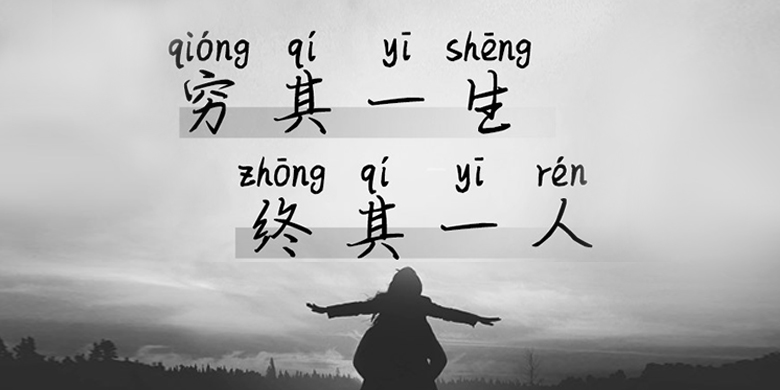
方正手迹-穷其一生终其一人
方正手迹-穷其一生终其一人,这款字体结构工整、笔画清晰,兼顾美观与易读性,适用于标题、正文、海报、包装、LOGO 等多种场景。字形优雅稳定,风格百搭耐看,适配日常排版与创意设计,让文字呈现更舒适、更具质感。方正手迹-穷其一生终其一人一笔一画,皆是细节,以均衡的比例、流畅的线条打造舒适视觉体验,字形端正大气,风格简约现代。无论是商业设计、品牌宣传还是日常排版,都能轻松驾驭,让文字更有格调与力量。方正手迹-穷其一生终其一人字体下载。
这是一款潇洒的手写体,笔画流畅转折圆润,既有坚硬刚强的感觉,又有圆润舒适的感觉。适用于现代诗歌、短文的排版以及文化、商业类品牌的广告语设计。